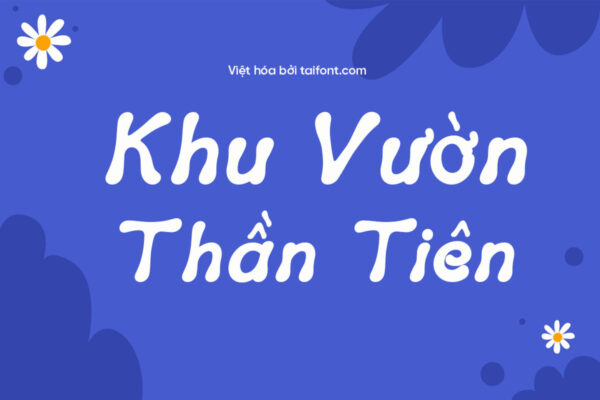
Tên font: Font Việt hóa VIP Kadera
Tác giả: Salamahtype
VIP Kadera Việt hóa là một font chữ không chân (sans-serif) nổi bật với thiết kế độc đáo và đầy tính tương lai, mang đến một phong thái hiện đại, công nghệ và đầy bí ẩn. Với những đường nét được trau chuốt, đôi khi sắc sảo, đôi khi mềm mại một cách lạ mắt, Kadera dễ dàng tạo ấn tượng mạnh mẽ, gợi liên tưởng đến những không gian vũ trụ rộng lớn và các công nghệ tiên tiến.
Font này là lựa chọn lý tưởng để bạn khám phá và thể hiện sự sáng tạo trong các thiết kế mang tính viễn tưởng và khoa học: